字体的演变
中国文字博大精深,而中国字体也是千奇百怪,而文字作为一种符号以形表意,以意传情,那么它是如何发展的呢。
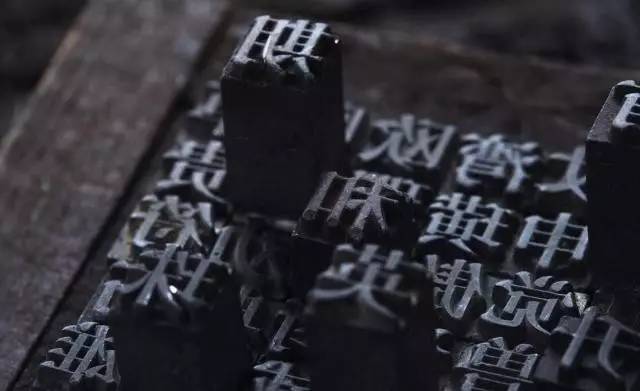
活字印刷
第一棒:甲骨文
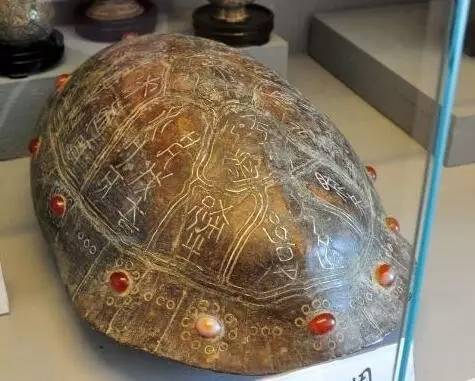
刻有甲骨文的龟壳
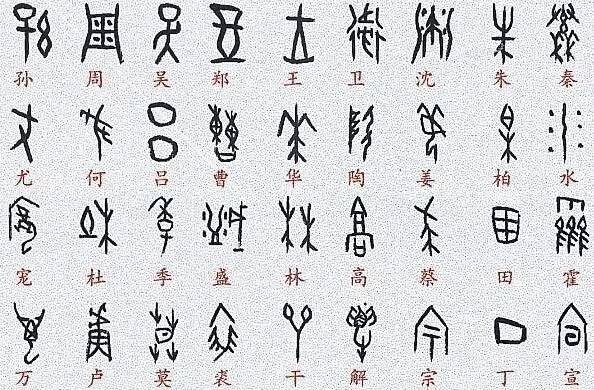
甲骨文
特点:而甲骨文即是象形文字又是表音文字,十分生动,它可是中国已发现古代文字中时代最早,体系最为完整的,较完整的记录语言。
朝代:它主要是中国商代后期,王室用于占卜,记事而刻在龟甲和兽骨的文字,也因此得名。
字库中代表字体:北师大甲骨文
第二棒:大篆
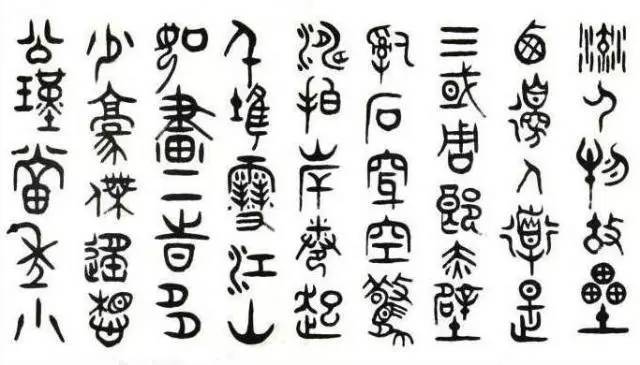
大篆
特点:线条化和规范化了,它逐渐脱离了图画的原型,有了方块字的基础
朝代:出现在西周后期,主要出现在青铜器上(钟鼎文)和石鼓(石鼓文),(PS.这两个均被称为大篆)
字库中代表字体:书体坊金文大篆
第三棒:小篆
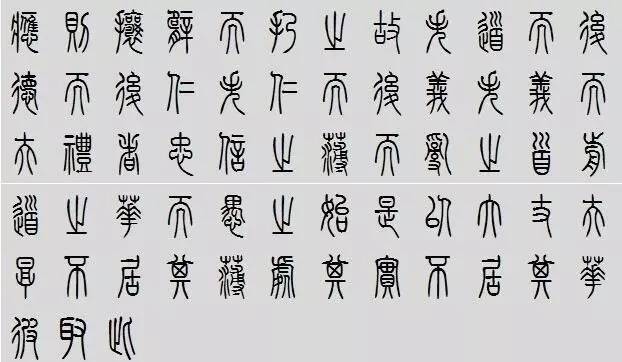
小篆
特点:几乎完全脱离图画文字,基本上是长方形的方块字体了,并且在转折处呈弧形
朝代:在秦朝统一六国之后,丞相李斯就把大篆去繁就简,改为小篆,形成全国统一文字
第四棒:隶书
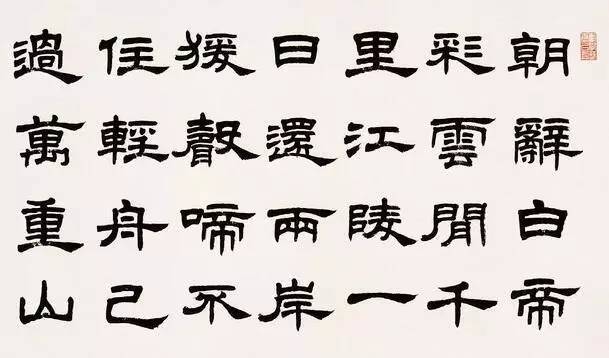
隶书
特点:在篆体的基础上,为适应书写而产生的字体,将小篆匀圆的字体变为了平直方正,并设有偏旁部首,而且隶书也是古今汉字的分水岭
朝代:产生于秦汉时期,也被较为“隶字”“秦隶”“汉隶”
第五棒:楷书
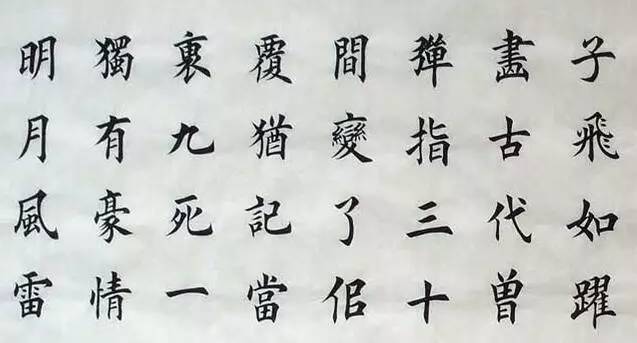
楷书
特点:《辞海》解释说它“形体方正,笔画平直,可作楷模”。这种汉字字体端正,就是现在通行的汉字手写正体字 。
朝代:楷书也叫正楷、真书、正书。由隶书逐渐演变而来,始于汉末,通行至今,长盛不衰。
字库代表字体:方正楷体等
第六棒:行书
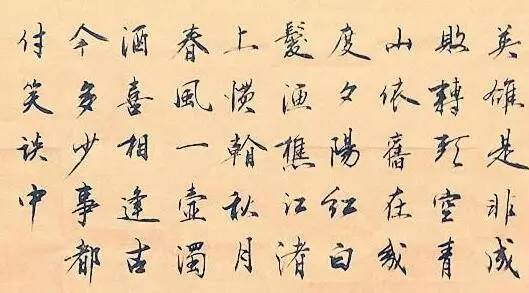
行书
特点:“行”是“行走”的意思,因此它不像草书那样潦草,也不像楷书那样端正。实质上它是楷书的草化或草书的楷化。楷法多于草法的叫“行楷”,草法多于楷法的叫“行草” 。
朝代:大约出现在西汉晚期和东汉初期。行书是一种统称,分为行楷和行草两种。它在楷书的基础上发展起源的,介于楷书、草书之间的一种字体,是为了弥补楷书的书写速度太慢和草书的难于辨认而产生的。
字库中代表字体:长城中行书、汉鼎简行书、书法家行书体、禹卫书法行书简体、文鼎中行书等。
第七棒:草书
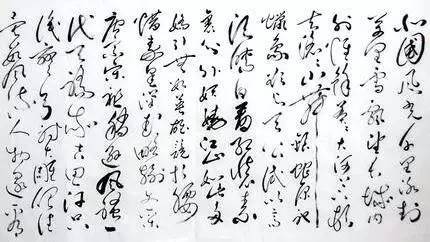
草书
特点:草书是汉字的一种字体,特点是结构简省、笔画连绵。形成于汉代,是为了书写简便在隶书基础上演变出来的。草书分为章草和今草,而今草又分大草(也称狂草)和小草
朝代:章草始创于东汉,而到了汉末,章草进一步“草化”,称为“今草”,今草书体自魏晋后盛行不衰。到了唐代,今草写的更加放纵,笔势连绵环绕,字形奇 变百出,称为“狂草”,亦名大草
字库代表字体;腾祥伯当草书、王羲之草书-深林流水书体
第八棒:印刷字体
印刷术发明后,为适应出版印刷,文字趋于横平竖直,横细竖粗,方方正正的宋体。而随着发展,宋体又衍生出长宋,扁宋,仿宋等字体,而西方印刷术传入后,黑体等多种有进入了我们的生活,当然,宋体至今依旧是主要的印刷字体。
黑体目前字库中可用的比较多,比如:方正黑体、方正兰亭黑体等。